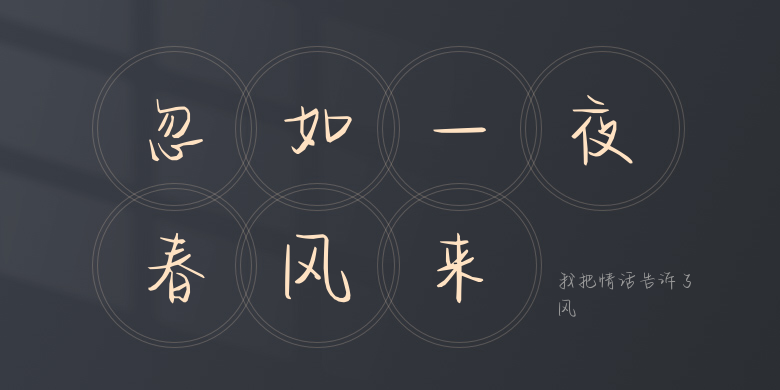
我把情话告诉了风
我把情话告诉了风,这款字体结构工整、笔画清晰,兼顾美观与易读性,适用于标题、正文、海报、包装、LOGO 等多种场景。字形优雅稳定,风格百搭耐看,适配日常排版与创意设计,让文字呈现更舒适、更具质感。我把情话告诉了风一笔一画,皆是细节,以均衡的比例、流畅的线条打造舒适视觉体验,字形端正大气,风格简约现代。无论是商业设计、品牌宣传还是日常排版,都能轻松驾驭,让文字更有格调与力量。我把情话告诉了风字体下载。